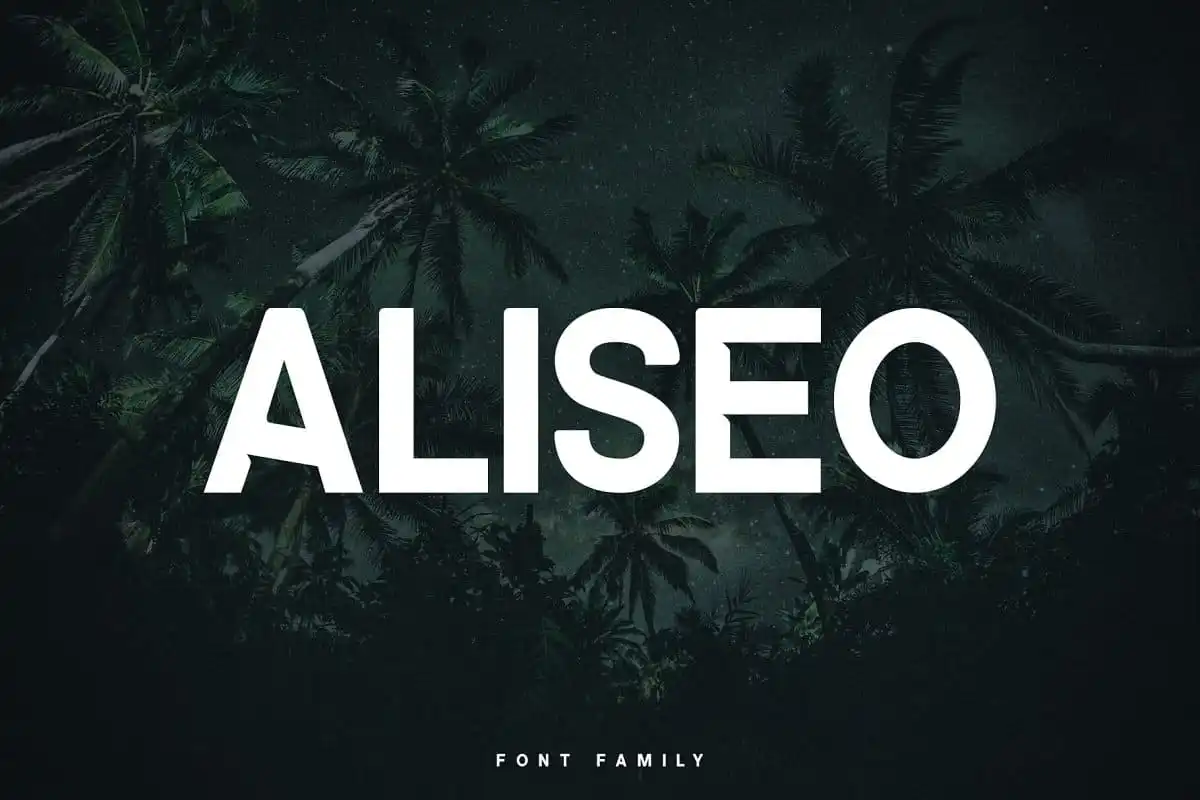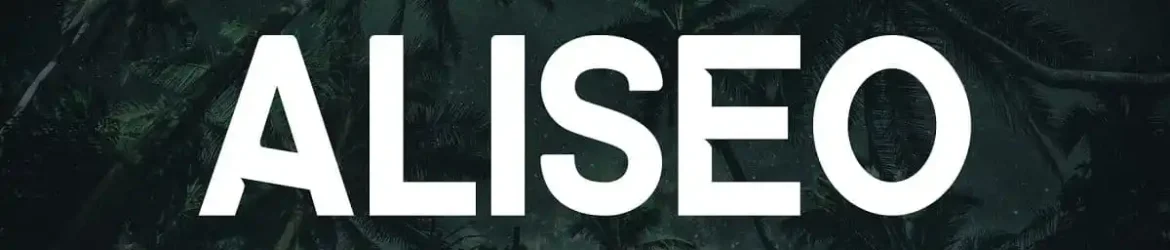
Olá pessoal! Introduzimos a Aliseo Sans Serif Font, uma nova família de tipo moderna e condensada. A Aliseo é um tipo sans serif forte e limpo, projetado para criar marcas e identidades visuais clássicas e fortes. É versátil o suficiente para ser usada em diversos contextos, desde logos e revistas até embalagens de produtos e designs de roupas. A Aliseo é perfeita para qualquer tipo de projeto visual que você possa imaginar. Seja um site de header ou um conceito de roupa fashionista: a Aliseo é uma fonte versátil e ideal, para ajudar a dar vida aos seus projetos. Não hesite em baixar o download da sua font favorita!